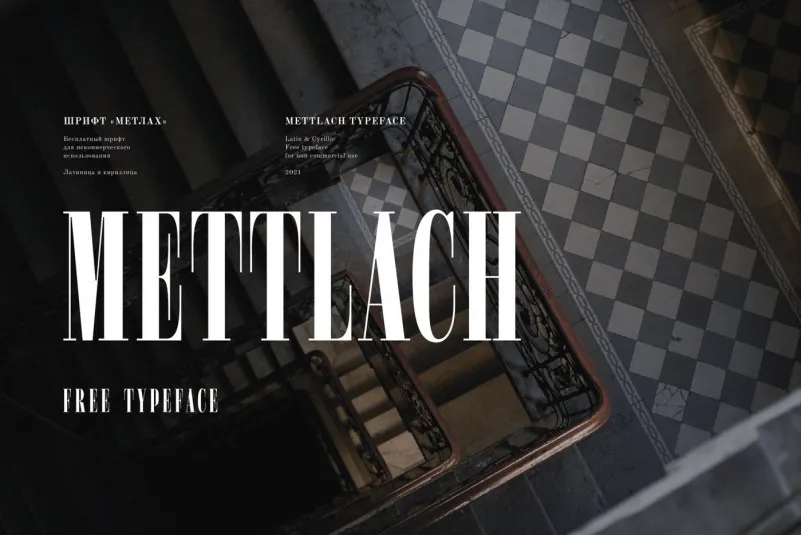
A Mettlach Font é uma elegante fónt que combina características serifadas com detalhes delicados. Criada pelo sartstudio, essa tipografia imita os designs dos anos passados, mas possui origem moderna e contemporânea. Sua influência clássica está presente na forma arredondada dos “drops” (cascata), que agora são mais afiadas, com a maioria das linhas oblique tendendo para um mesmo ângulo de inclinação. Com contraste alto e perfilado, essa fonte faz uma aparição bem estilosa em cabeçalhos. Ideal tanto para textos profissionais quanto para aplicar na identidade visual de projetos contemporâneos. Experimente ela no seu próximo projeto e veja como sua tipografia ganha um toque sofisticado e moderno.